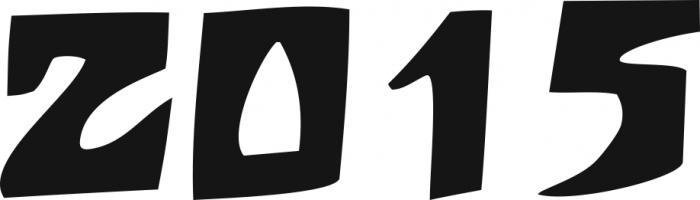
[Mitglied Ibot…] Geschrieben Mai 4, 2016 Teilen Geschrieben Mai 4, 2016 Hallo, bräuchte bitte eure Hilfe bei folgender Schrift. Danke für eure Hilfe. Liebe Grüße! Link zu diesem Kommentar
Beste Antwort [Mitglied Gizz…] Geschrieben Mai 4, 2016 Beste Antwort Teilen Geschrieben Mai 4, 2016 http://www.azfonts.net/load_font/tarzan.html 1 Link zu diesem Kommentar
[Mitglied c128…] Geschrieben Mai 4, 2016 Teilen Geschrieben Mai 4, 2016 http://www.azfonts.net/load_font/tarzan.html I must say, to an extent it actually looks like “Waldorf meets Jungle” Link zu diesem Kommentar